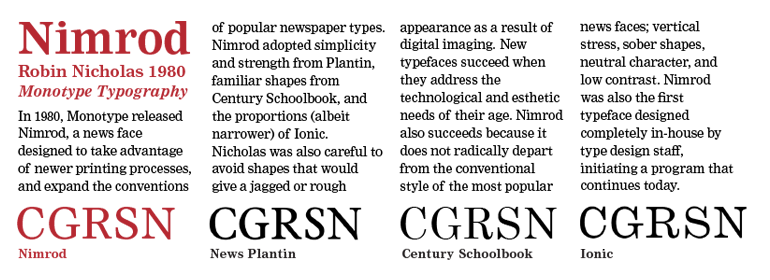
Nimrod®
Nimrod由Monotype于1980年发布。Nimrod字体家族是针对当前报纸技术而设计的,它是对报纸行业需求进行广泛研究的结果。Nimrod保留了传统报纸Ionics的许多功能,但一些琐碎的细节已被更旧的样式(例如Plantin)所取代。高度清晰的字体家族,尤其是较小的字体,其清晰明确的字符形状使文本块易于阅读。 Nimrod还可以承受报纸生产和印刷中遇到的退化。 Nimrod字体家族最早用于Leicester Mercury报纸的正文,后来成为报纸文本和标题的流行之选。
Nimrod was released by Monotype in 1980. Designed for current newspaper technology, the Nimrod font family evolved as a result of extensive examination of newspaper industry needs. Nimrod retains many of the features of the traditional newspaper Ionics, but some of the fussier detailing has been replaced by the more sober forms of the old styles, such as Plantin. A highly legible font family, especially in smaller sizes, its clear unambiguous character shapes make easily readable blocks of text. Nimrod also withstands the degradation encountered in newspaper production and printing. First used for body text in the Leicester Mercury newspaper, the Nimrod font family has subsequently become a popular choice in newspapers for text and headlines.